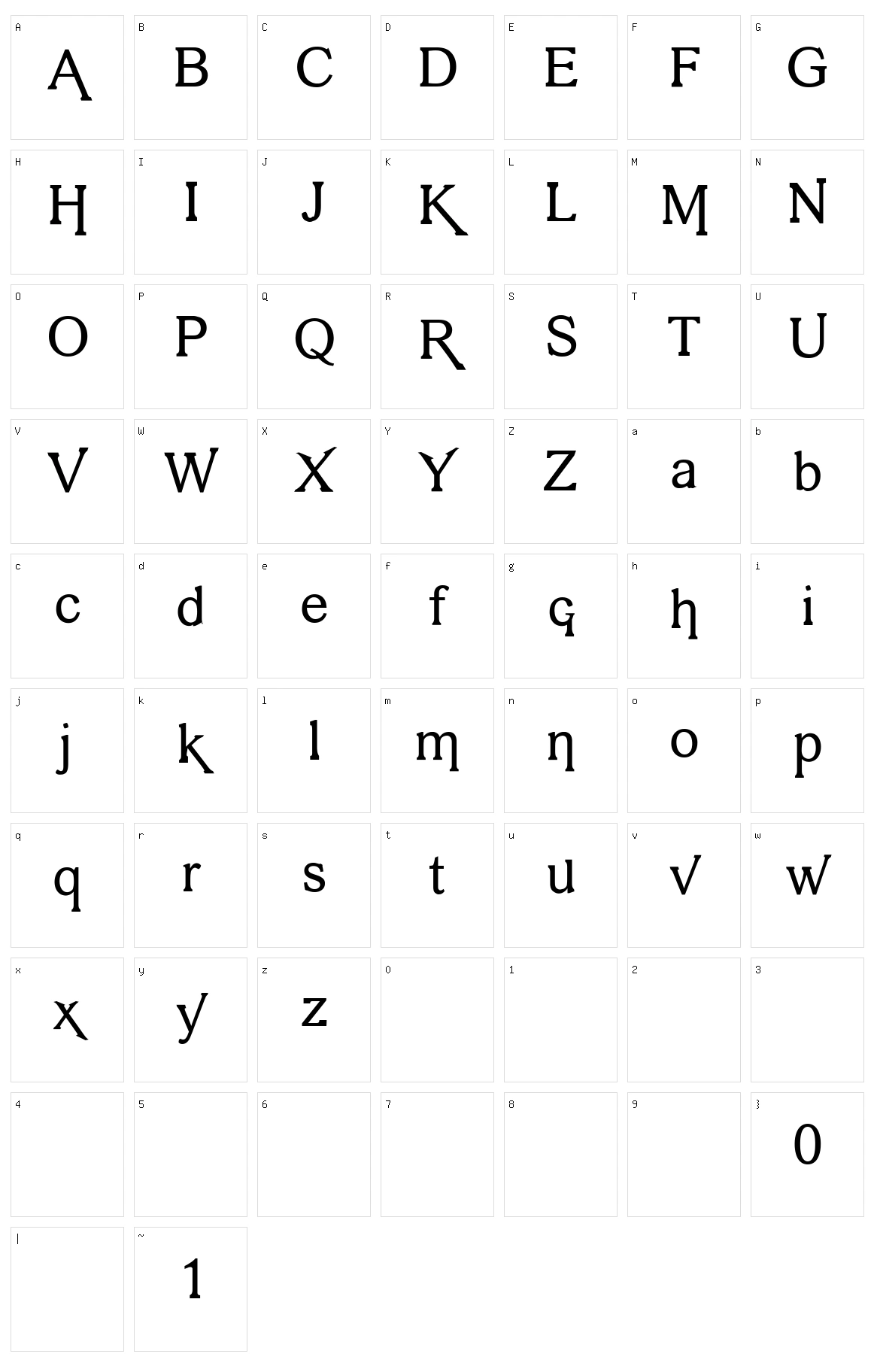
VENGEANCE PW
primeiro trabalho de Paulo W na area de fontes para texto. contudo, esta fonte tem caractersiticas display peculiares que podem ser bem aproveitadas em titulos e publicidade, com o uso das letras maiusculas.
Olá, sou designer gráfico especialista em identidade corporativa e logotipia. Mas o design e o estudo de tipologias e escritas cursivas caligráficas (históricas e contemporâneas) ocupam boa parte de meu tempo e predileções diletantes. Espero que tenha gostado desta fonte, um de meus primeiros trabalhos, que ainda estão sendo aprimorados.
Hello, I am a graphic designer, specialist in corporate identity and logotipy. But the design and the study of typologies and calligraphic cursive writing (historical and contemporary) occupy a good lot of my time and dilettante predilections. I hope you like this font, one of my first works, which I am still improving.